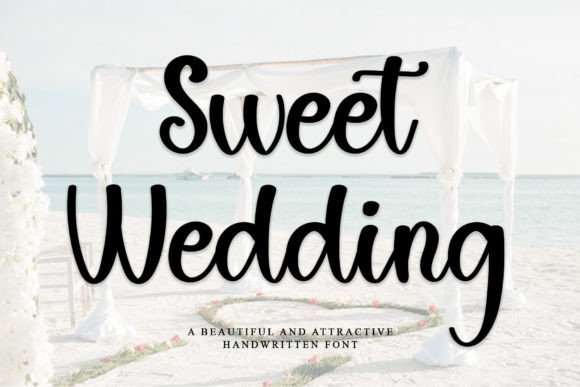
Sweet Wedding
Si buscas recursos de alta calidad como Sweet Wedding, este paquete premium es una opción fantástica para tus proyectos creativos.
Elaborado con precisión, Sweet Wedding proporciona vectores limpios, tipografía suave y una licencia comercial para tu tranquilidad.
Ya sea que estés creando productos POD (impresión bajo demanda), invitaciones de boda o gráficos para redes sociales, Sweet Wedding es una opción ideal.